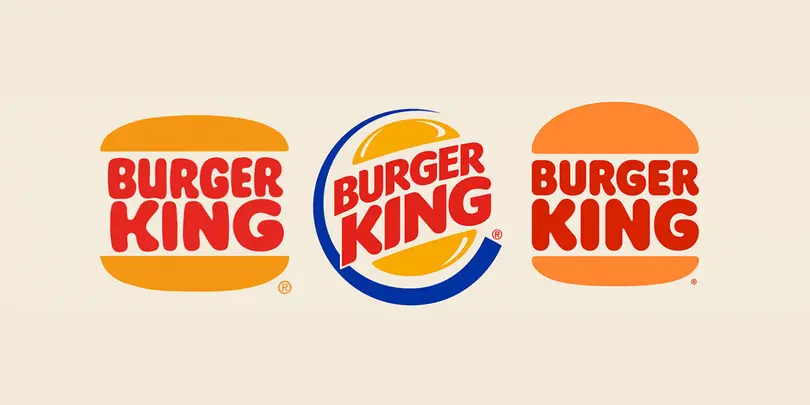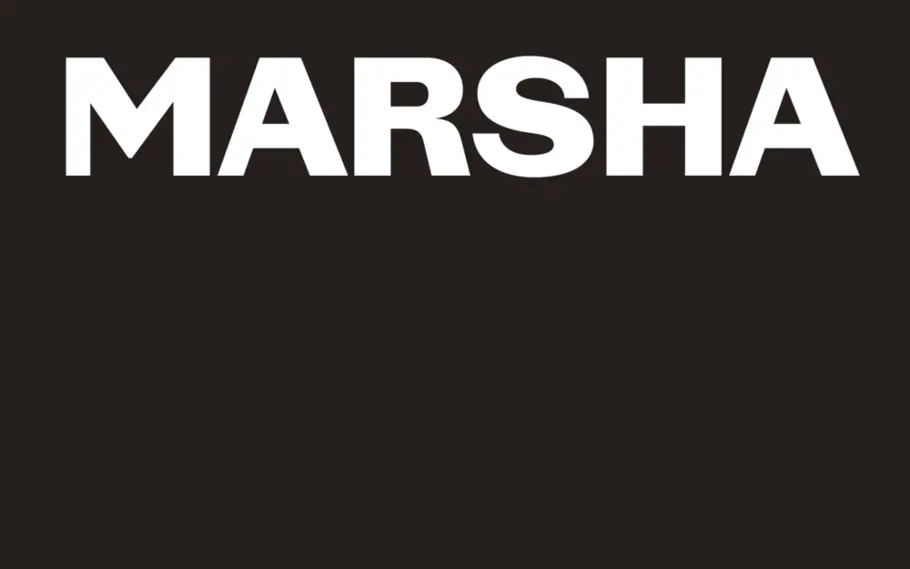
Le renouveau du rétro : focus sur la nostalgie dans le design.
Alors comment faire revivre les éléments de design ludiques et réconfortants du passé, sans ignorer les vérités douloureuses de ces époques ?
La nostalgie, une alliée pour faire face en temps de crise, a le vent en poupe dans toutes les disciplines du design. Par quoi est motivée cette tendance et quelles sont les complexités liées à la renaissance d’éléments de design historiques ?
Ces deux dernières années, vécues comme les plus incertaines par la plupart d’entre nous, la nostalgie s’est immiscée dans de nombreux aspects du quotidien – la mode, le mobilier et même la musique écoutée en streaming. À travers les identités de marque, notamment, nous avons aussi pu observer le branding et le design chercher à créer un sentiment de sécurité en réinventant ce qui était familier. Cette logique est scientifique. Les psychologues ont en effet découvert que les réminiscences peuvent aider les gens à surmonter les crises.
À l’instar des antiquaires, les designers sont passionnés par les archives. Plonger dans des logos historiques, de vieux livres, d’anciennes affiches, c’est trouver des trésors d’inspiration auxquels rendre hommage. Combien de polices récentes sont inspirées par les lettres d’un vieux livre découvert chez un bouquiniste ou par une vieille carte postale trouvée lors d’un vide-grenier ? Ceci est une façon de célébrer les icônes ou de créer un style unique – que ce soit pour un logo ou pour chez soi.
La dernière publication du Studio Monotype, une police serif contemporaine appelée Cotford, et conçue par le directeur de la création typographique Tom Foley, comporte elle-même une touche de nostalgie. « Cotford reflète une expérience vécue par la plupart des gens pendant les points culminants des confinements : un désir de confort familier et de chaleur dans toute cette incertitude. »
Le frisson de la découverte.
Au-delà du design graphique et typographique, le style rétro a gagné en popularité dans le mobilier, la décoration d’intérieur et la mode. Le rituel de trouver une pièce ancienne et rare pour lui redonner vie dans le monde moderne a offert un soulagement pendant la pandémie et s’est développé grâce aux nouveaux canaux, comme Instagram, et aux sites de revente en ligne, comme Vinted.
La mode a toujours fonctionné par cycles. Mais selon ThredUp, une boutique de revente en ligne, la friperie est récemment devenue une industrie de 36 milliards de dollars et pourrait détrôner la fast fashion d’ici 2025. L’attention accrue à la durabilité a poussé des foules de jeunes consommateurs à se tourner vers l’occasion plutôt que d’opter pour le neuf. La pandémie a aussi causé plus d’un souci dans les chaînes d’approvisionnement de presque tous les secteurs. De nombreux consommateurs préfèrent la satisfaction instantanée d’une friperie à l’attente d’un envoi tardif d’une marchandise neuve.
La chasse aux trésors vintage s’étend à l’habitat, comme l’a expliqué le photographe Tyler Haughey dans notre podcast. Son travail porte sur certains éléments, comme les vieilles enseignes ou les anciens décors, et étudie comment ils ancrent les expériences et les souvenirs dans notre esprit. « Les souvenirs sont d’abord très familiers, récents, tangibles. Puis, à mesure que l’on s’en éloigne, ils prennent un aspect plus étrange, fantasmagorique. Je pense que c’est la nature même de la mémoire que de devenir de moins en moins précise avec le temps », explique Tyler.
Qu’il s’agisse de polices arrondies des 70’s, de photos floues de stations balnéaires disparues, de jeans devenus fripes ou de meubles anciens, tous ces éléments peuvent servir de vecteur pour raconter des histoires ou redonner vie au passé. Dans notre rapport des tendances typographiques 2021, nous avons identifié pour la première fois la tendance des serifs doux « soft serve », après avoir noté l’apparition de caractères douillets et nostalgiques influencés par Cooper Black dans les rebrandings de Chobani (InHouse), MailChimp (Collins), Meridian (BulletProof), Dunkin et Burger King (JKR). Après une nouvelle année sans relâche, la tendance s’est renforcée. Elle se manifeste par des caractères avec des ornements ludiques, des serifs épais, des lettres excentriques et des combinaisons de couleurs vibrantes.
Le rebranding de Burger King par JKR.
Célébrer la diversité du passé.
Ce qui peut toutefois devenir délicat, c’est lorsque l’appréciation de l’élément de design historique est séparée du contexte social, parfois déplaisant, dans lequel il a été créé. « Cet enthousiasme pour la nostalgie nous laisse enclins à tout voir en rose et à faire du “cherry-picking”, c’est-à-dire à ignorer le sexisme, le racisme, les inégalités sociales et à dire : “Il fut un temps où les hommes blancs pouvaient jouer au baseball” » a souligné Charles Nix, directeur de la création typographique chez Monotype, dans une interview pour Print Mag à propos de la résurgence du design rétro des uniformes sportifs.
Alors comment faire revivre les éléments de design ludiques et réconfortants du passé, sans ignorer les vérités douloureuses de ces époques ?
Pour en revenir à la typographie, penchons-nous sur le travail de Tré Seals, fondateur et propriétaire de Vocal Type qui utilise les polices comme outil de narration. Toutes les typographies de Vocal sont inspirées d’événements historiques tels que des manifestations et mouvements de protestation, et portent le nom d’éminents défenseurs de la justice sociale, notamment Marsha P. Johnson, Martin Luther King, and Bayard Rustin.